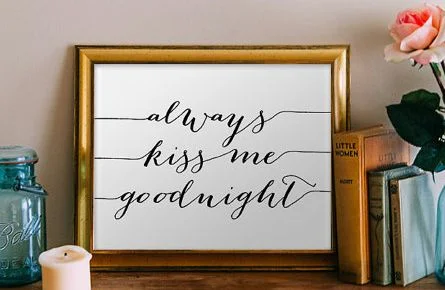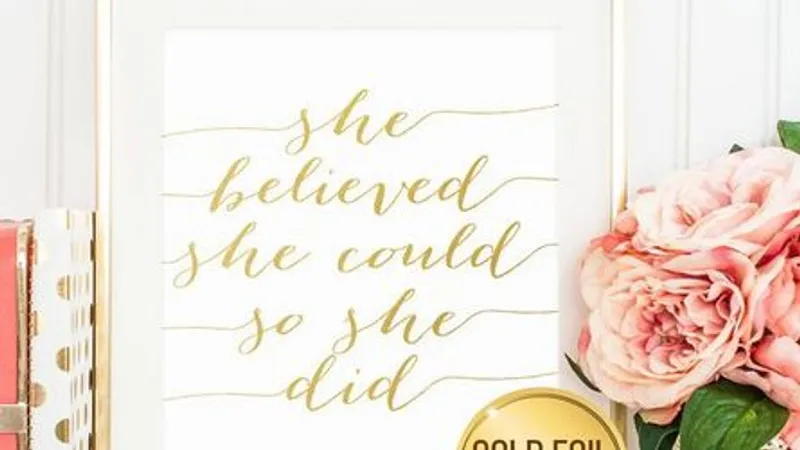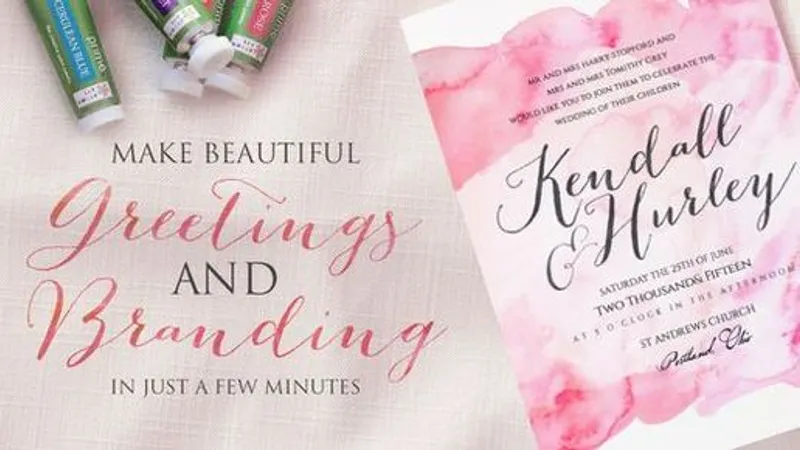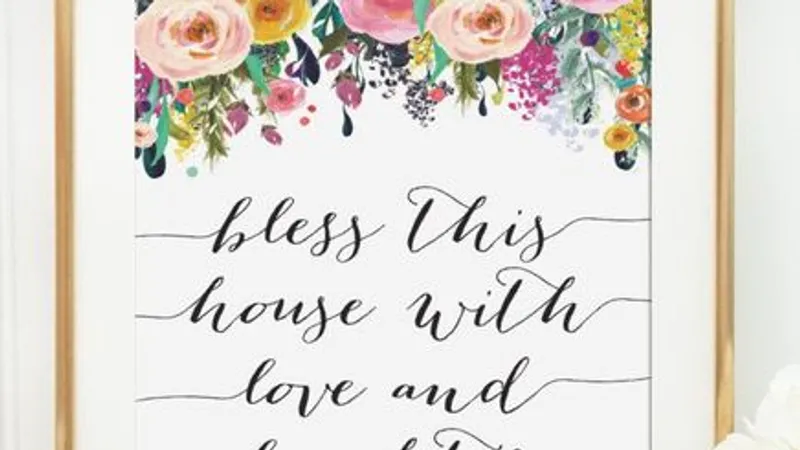
Bombshell Pro - Рукописный МЕГАпопулярный на Etsy шрифт
Данный продукт представляет собой профессиональный графический актив — популярный шрифт, востребованный на международной торговой площадке Etsy. Это готовый к использованию цифровой инструмент для дизайнеров, оформителей и создателей контента, который позволяет придать текстовым элементам уникальный и эстетичный вид.
• Высокая популярность и востребованность в коммерческом дизайне на платформе Etsy.
• Наличие большого количества разнообразных глифов, что расширяет возможности типографики.
• Возможность использования в различных графических редакторах для создания логотипов, брендинга, оформления социальных сетей и печатной продукции.
• Высокое качество прорисовки символов, обеспечивающее профессиональный вид готовых работ.